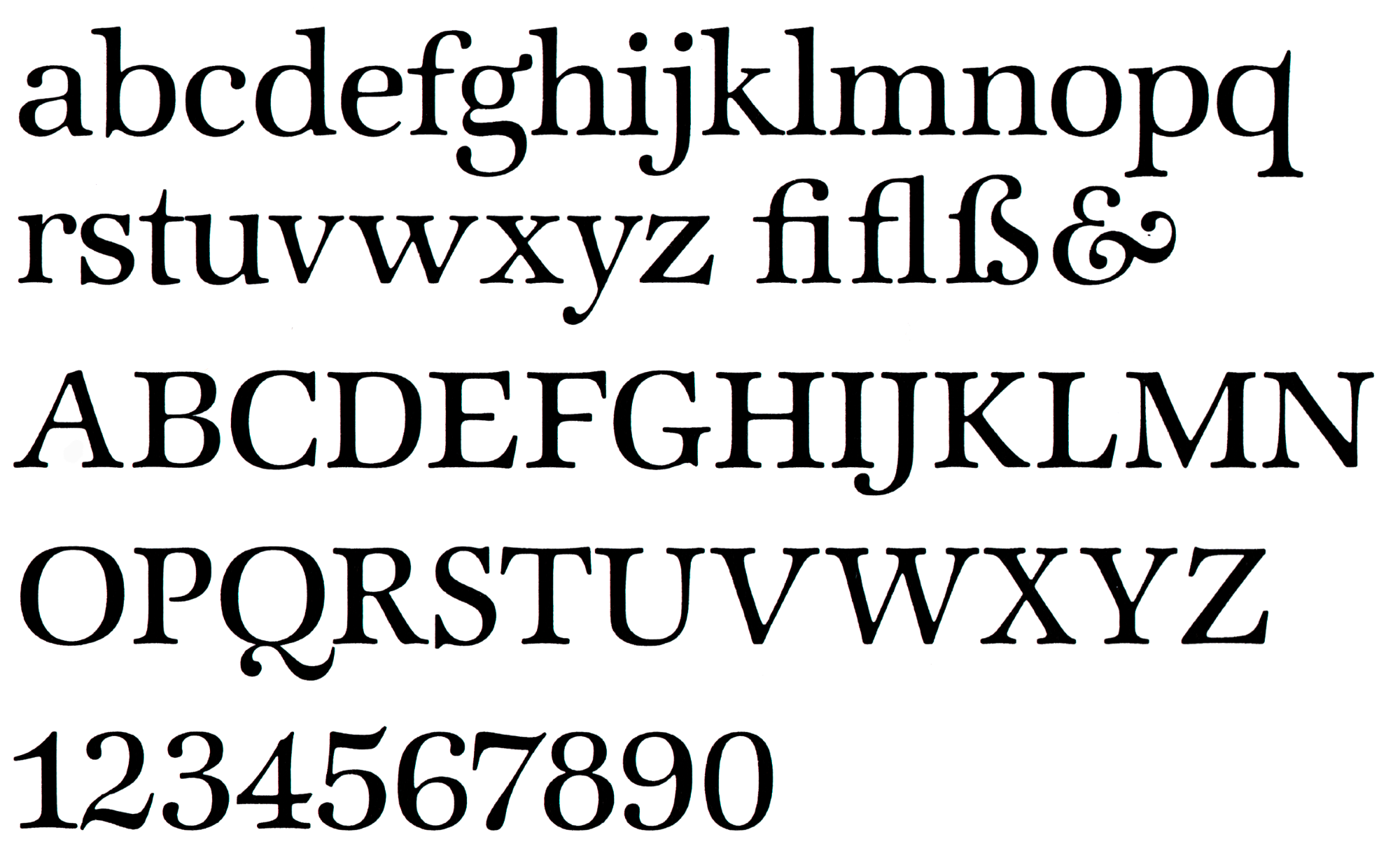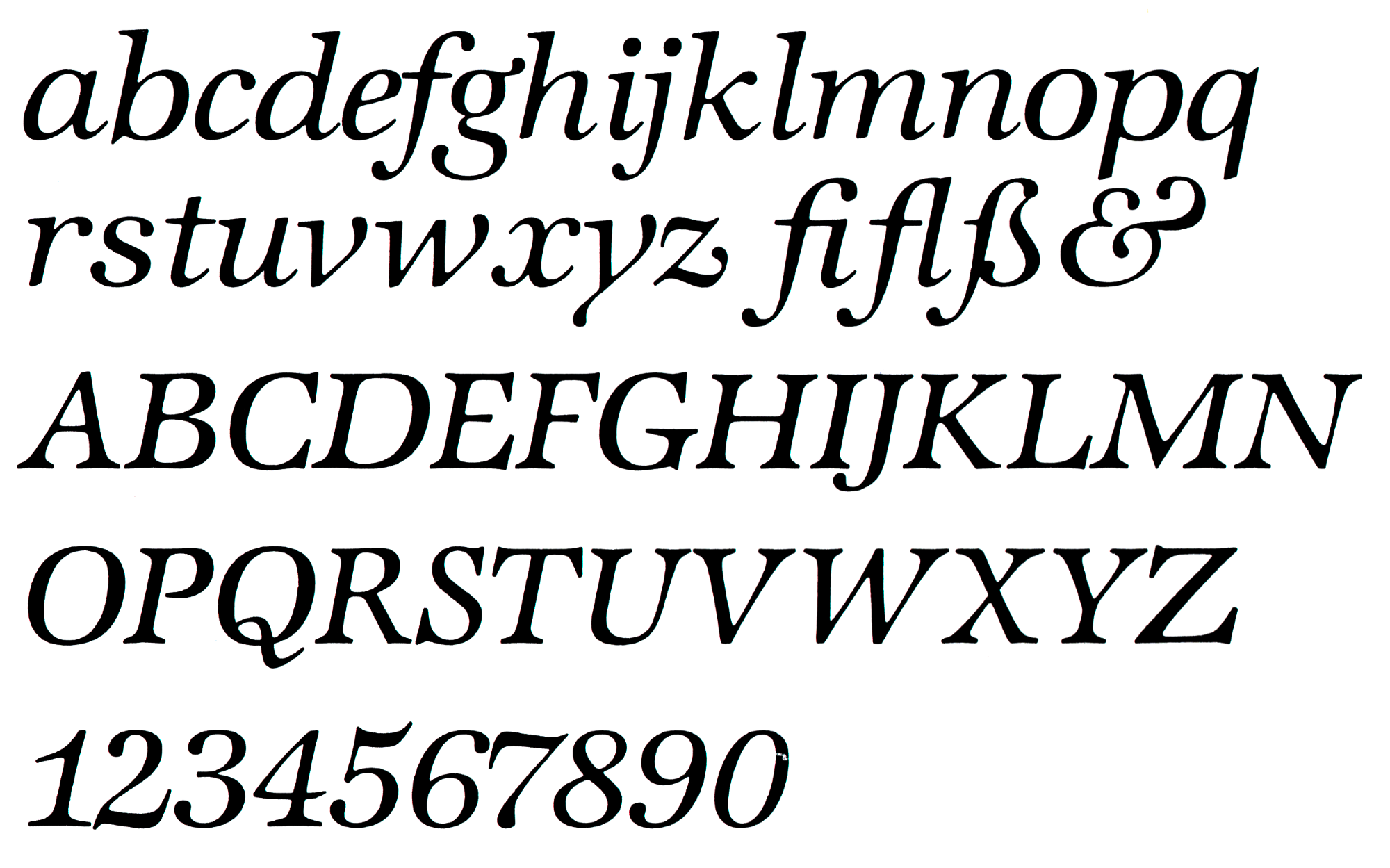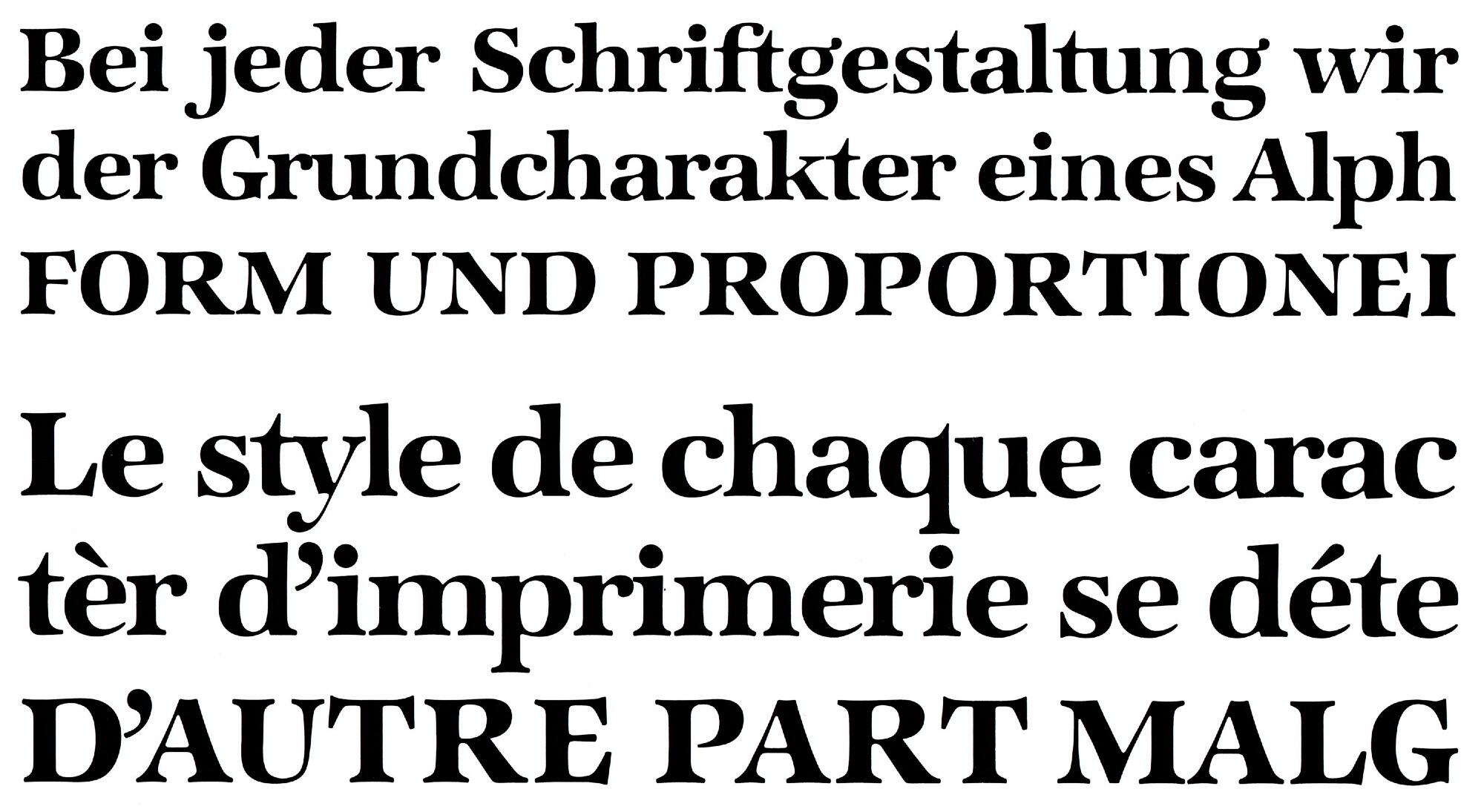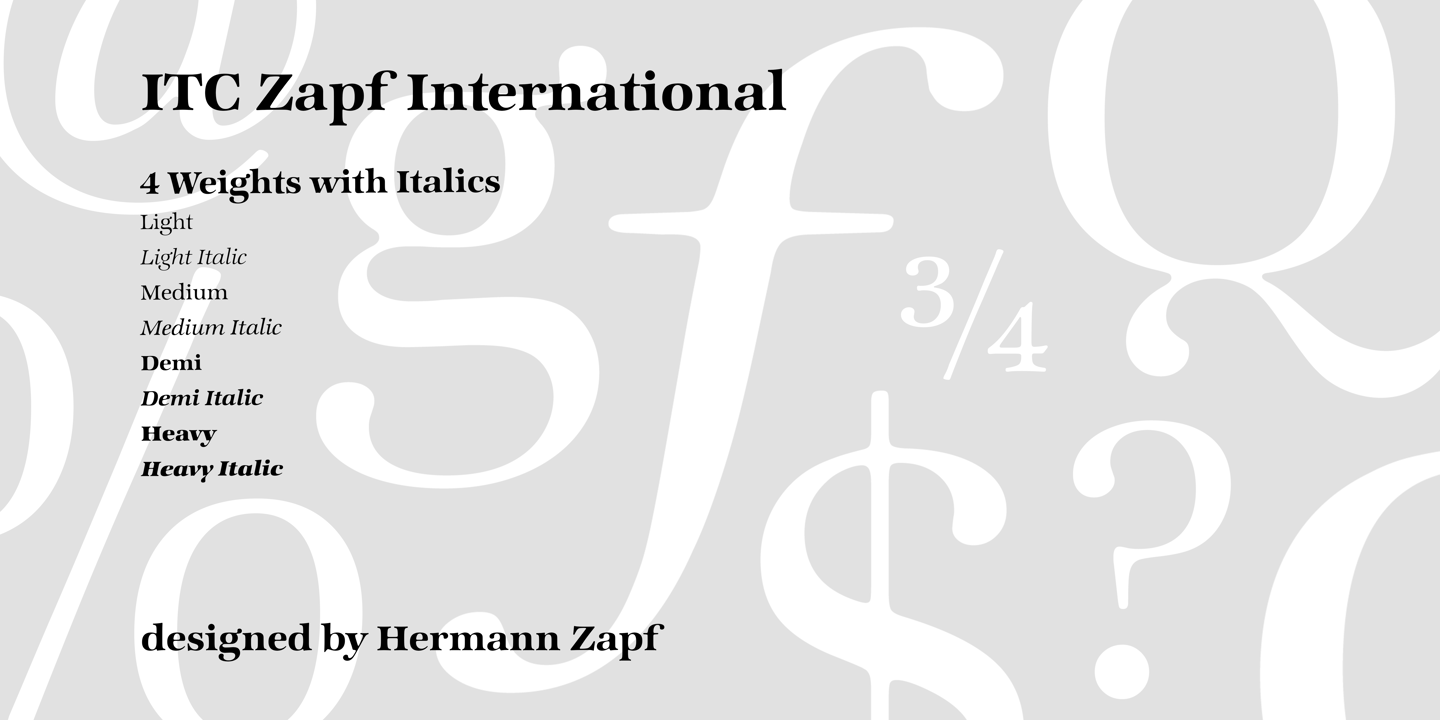
Font-Wiki: ITC Zapf International
Die Zapf International von Hermann Zapf erschien in den 1970er-Jahren als Fotosatzschrift bei der International Typeface Corporation. Die Familie verfügt über vier Strichstärken mit zugehörigen Kursiven.